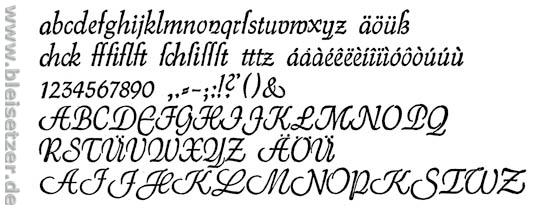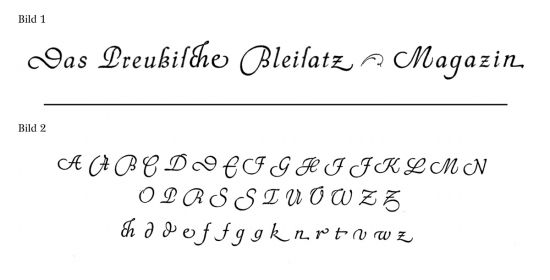
Schriftenausstattung erstellen.
Im Bleisatz ist es nicht anders als in Eurer Welt der digitalisierten Schriften: Man versucht, eine sinnvolle Zusammensetzung seiner Schriften zustande zu bringen.
Dabei gibt es ein paar Umstände, die man berücksichtigen muß und die Euch keine Probleme bereiten:
- Der Platz ist begrenzt.
Eine Bleisatz-Gasse besteht aus zwei Doppelschränken mit jeweils 14 Brotschrift- und 14 Steckschrift-Schubladen.
- Bleisatz-Schriften sind teuer.
Die Steckschrift-Kästen kann man gut mit gebrauchten Schriften bestücken. Die sind nicht so furchtbar teuer, sofern man viel Geduld hat.
Das Problem sind die Brotschriftgrade von 6 p bis 14 p einschließlich.
Grundsätzlich habe ich sehr schöne Auszeichnungsschriften: Antiqua-Varianten, Gebrochene, sehr viele Jugendstil-Schriften.
Als Brotschriften habe ich die:
- Helvetica leicht
- Futura Buchschrift
- Weiß Antiqua
Irgendwann, wenn ich mich einmal endgültig entschieden habe, werde ich mir noch eine zweite Antiqua-Reihe von 6 p bis 14 p zulegen. Aber da wüßte ich im Moment noch nicht, welche.
Nun das konkrete Problem:
Ich brauche als Ergänzung eine Schreibschrift.
Sie muß klassisch schön sein und am besten zeitlos.
Natürlch paßt sie zu meinen Brotschrift-Familien, aber ich möchte sie auch mit meinen Auszeichnungsschriften mischen können - bis hin zu einer Kombination mit Jugendstil-Schriften.
Nun tendiere ich zur Gavotte:
Gebr. Klingspor, Offenbach am Main
Erstguß 1940
Rudo Spemann
Es gibt da gerade die Möglichkeit, relativ günstig an neu gegossene Schnitte heranzukommen.
Was sagt Ihr denn zu den Möglichkeiten, diese Schreibschrift mit den oben genannten Schriften zu kombinieren?
So rein geschmacklich: Mit der Helvetica würde ich das nicht kombinieren wollen, mit der Futura könnte es sehr schön aussehen. Mit der Weiß müsste man's mal ausprobieren, könnte ich mir aber gut vorstellen, wenn die Charakteristik der Serifen irgendwie harmoniert.
Mir geht es eher um die Kombinationsmöglichkeit der Gavotte mit anderen Auszeichnungsschriften wie Antiqua-Varianten, Gebrochenen oder gar Jugendstil-Schriften.
Das Problem bei den Jugendstil-Schriften ist, daß man sofort sehr eingeschränkt ist bei der Kombination. Andere Jugendstil-Schriften harmonisieren meist gar nicht, weil beide so starke Charaktere haben. Somit führt mich meine Liebe zu diesen Schriften in eine Sackgasse. Wonit ich aber leben werde.
Eine Schreibschrift brauche ich. Die meisten empfinde ich als entweder zu langweilig oder aber zu häufig eingesetzt:
Die Gavotte nun erscheint mir als sehr schön und ausgeglichen, aber auch mit einem starken eigenen Charakter. Und gleichzeitig mit anderen Auszeichnungsschriften kombinierbar.
So gesehn hast du recht. Schön, dass es diesen zweiten Satz (Schwung-)Versalien gibt.
Wie sähe das aus?
Die obere ist die Lang-Schrift von 1905.
Ist zwar Jugendstil, aber (für mich) auch irgendwie reformhausanthroposophisch. Abgesehen davon, ist es keine angenehmer Kontrast zwischen eckig (Jugendstilschrift) und rund (Schreibschrift). Persönliches Empfinden, rein irrational gesprochen.
Tut mir leid. Mir fehlt die Bildung, um überhaupt zu verstehen, ob Du mir nun zu- oder abrätst.
anthropologische schriften. siehe weleda-logo:
ne, bleib mal bei der gavotte.
wozu brauchst du die nochmal?
was hast du noch zur auswahl?
Nochmal kurz:
Ich habe viele solcher Schriften wie Lang-Schrift.
Was ich bisher überhaupt nicht habe, ist eine möglichst vielseitig einsetzbare Schreibschrift.
Möglichst einsetzbar bedeutet:
- Alleine in unterschiedlichen Graden
- Kombinierbar mit Helvetica leicht, Futura Buch oder Weiß Antiqua
- Vielfältig einsetzbar
Und da kam mir die Gavotte in den Sinn. Ich kenne und mag sie schon sehr lang. Und Stempel bietet gerade ein Sonderangebot an.
Ansonsten gibt es schon Auswahl genug. Aber die gefallen mir entweder nicht oder aber sie sind nicht gut kombinierbar (siehe oben):
Meiner Meinung nach ist die Kombination von Jugendstil-(Auszeichnungs-) Schriften und Schreibschrift grundsätzlich problematisch. Wenn Du Dir einmal den Einsatz von Jugendstilschriften in zeitgenössischen Druckwerken ansiehst, wirst Du sehen, dass als Fließtext gerne eine zurückhaltende, neutrale – ›dunkle‹ – Antiqua gewählt wird, die die blumigen Auszeichnungen erst recht zur Geltung bringen lässt. Kursive Schreibschriften und Jugendstil – das beißt sich m. E. zu stark. Für mein Empfinden eignet sich die Gavotte auch nicht einmal zusammen mit Futura oder Weiß – aber dies ist dann Geschmackssache.
Falls noch nicht bekannt und für das Tagebuch interessant:
Das oben aufgeführte Zitat ist im Original etwas länger und es gibt eine
wunderschöne Beschreibung zu Rudo Spemann und seiner Gavotte von
Walter Tiemann in >Beseelter Kalligrapie<.